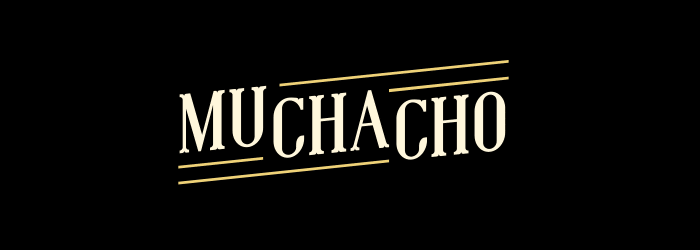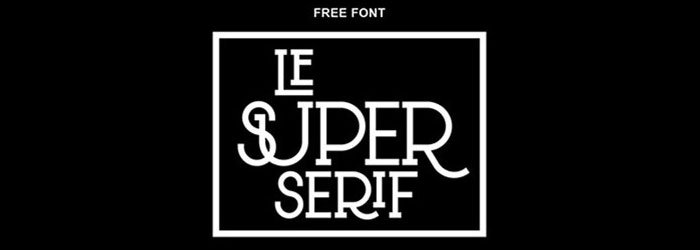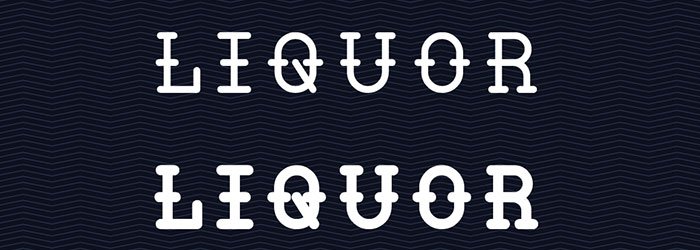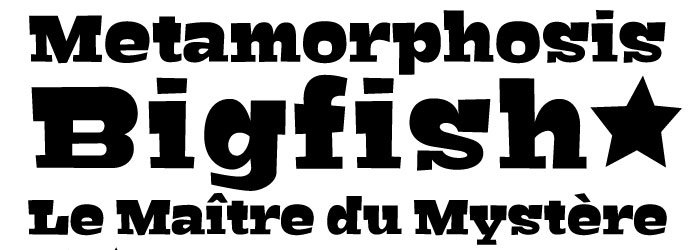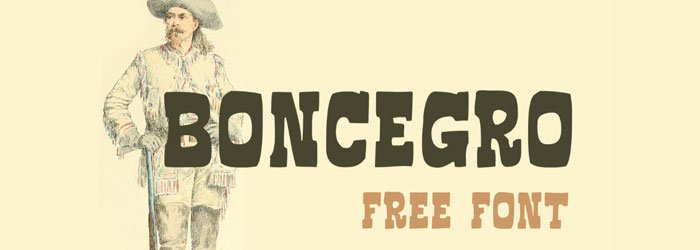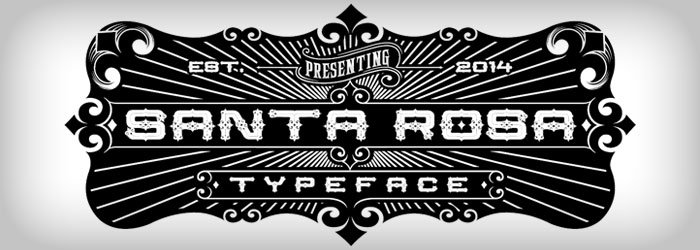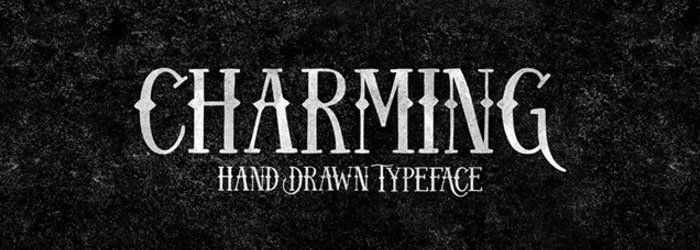
30 fontes estilo Velho Oeste gratuitas para download
Muitas vezes precisamos de fontes com temas específicos para algum trabalho ou projeto pessoal. É o caso de fontes no estilho velho-oeste ou faroeste.
Se você procura por fontes gratuitas com temas relacionados a cowboys, xerifes, saloons, cactos, botas e cartazes de procurado, chegou ao lugar certo.
Selecionamos nada menos que 30 fontes desse estilo para você utilizar em seus projetos.
Weston
Cow Cow
Muchacho
Le Super Serif
Liquor
Bigfish
Oldways
BLNC
Boncegro
Western FreeHand
Erster Caps
Santa Rosa
Charming
Rio Grande
Bleeding Cowboys
Nashville
Pistolgrip
Henry Rodeo Circus
Old Milwaukee
Candy
Barn
Young Heart
Dust West
Los Banditos
Rancho
Gunfighter Academy
The Dead Saloon
ChunkFive
Edmunds
Zantroke